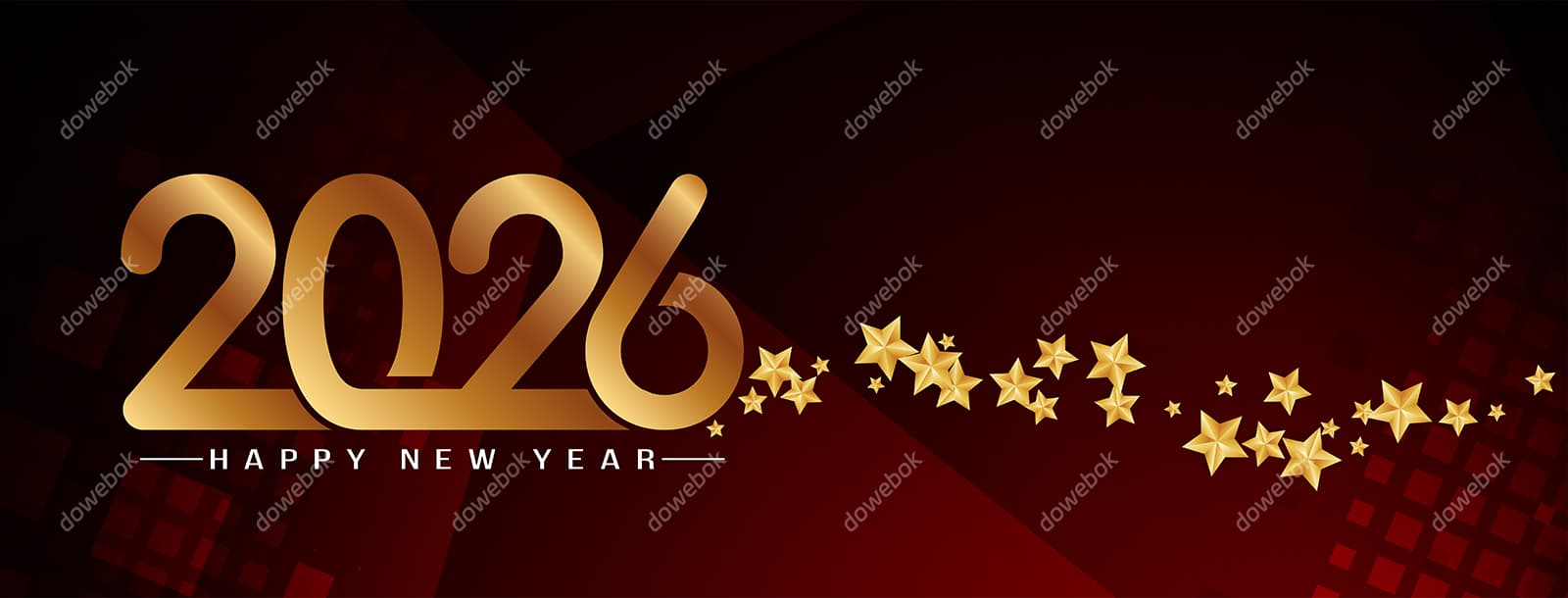
这是一款星星点缀和金色数字设计的 2026 新年快乐 banner 矢量素材,深红暗纹背景上,“2026” 以光泽感金色字体呈现,质感华贵。数字旁延伸出一串金色星星,与背景的几何暗纹呼应,下方配白色 “Happy New Year” 英文(衬以细黑线装饰)。整体红金配色浓郁喜庆,星星元素添了灵动,既显新年热烈氛围,又有精致的设计感。